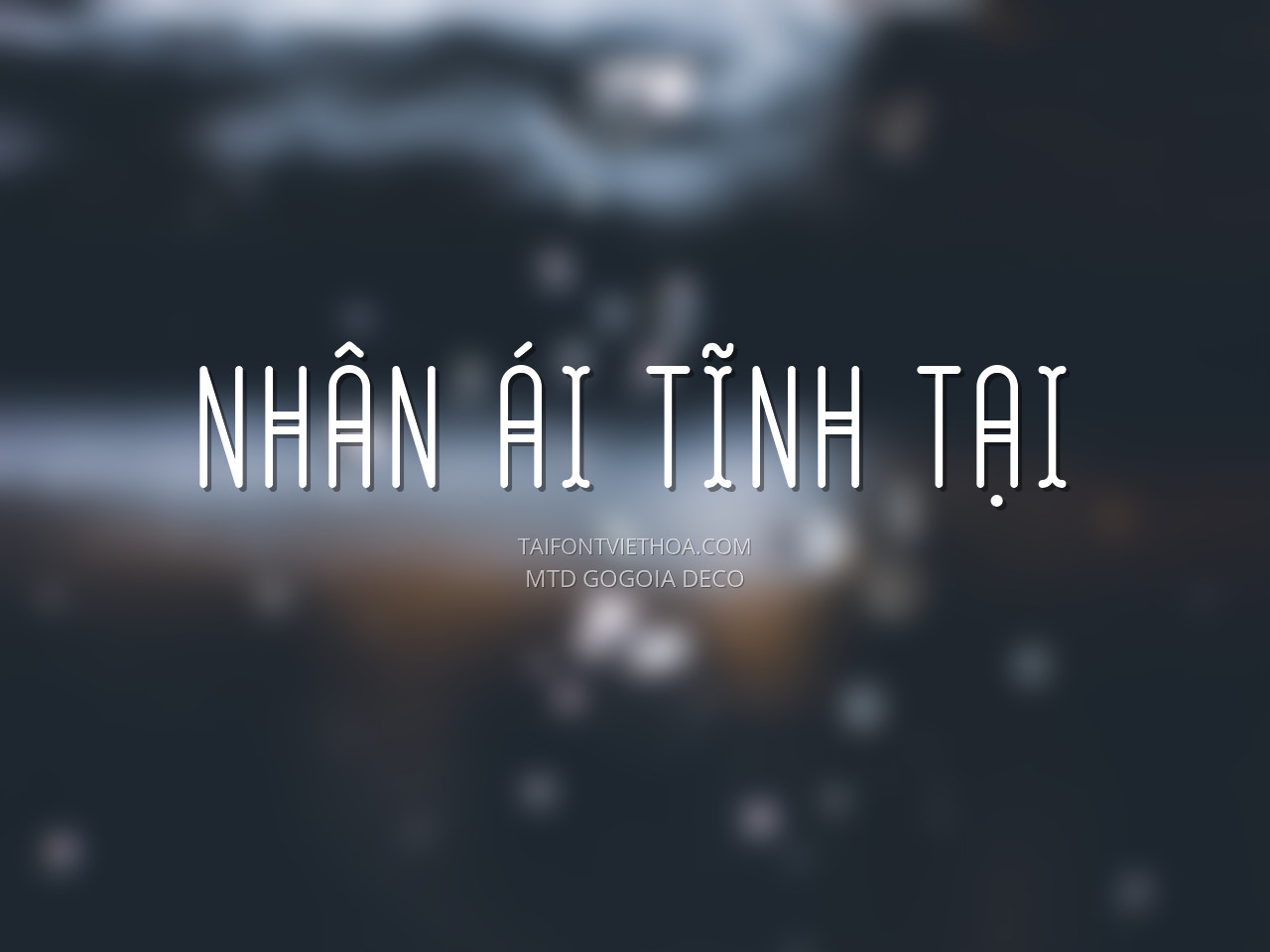
Giới thiệu về font Gogoia Deco
Gogoia Deco là một font display mang đậm phong cách hình học và nghệ thuật Art Deco, được thiết kế bởi Motokiwo Type (MTD). Font thể hiện sự kết hợp táo bạo giữa các khối hình học tối giản và tỷ lệ chữ lạ mắt, tạo nên cảm giác hiện đại, thời trang nhưng vẫn gợi nhớ nét hoài cổ của thập niên 1920–1940. Gogoia Deco không chỉ là một kiểu chữ mà còn là một yếu tố đồ họa độc đáo, phù hợp với những dự án đòi hỏi sự sáng tạo và khác biệt. Phiên bản Việt hóa do chính MTD thực hiện, hỗ trợ đầy đủ tiếng Việt và hơn 70 ngôn ngữ khác, mang lại tính linh hoạt cao cho nhà thiết kế trong và ngoài nước.
Font Gogoia Deco được taifontviethoa.com chọn lọc và giới thiệu trong nhóm font display ấn tượng, hướng đến cộng đồng sáng tạo đang tìm kiếm sự nổi bật và phá cách. Đây là một font có khả năng truyền tải ngôn ngữ thị giác rất mạnh, phù hợp với các dự án thương hiệu cá tính hoặc thiết kế nghệ thuật đậm dấu ấn cá nhân.
Đặc điểm thiết kế và ứng dụng của font Gogoia Deco
Font sở hữu thiết kế dạng khối, với các đường thẳng và góc bo tròn tinh tế, tạo ra sự cân bằng giữa cứng cáp và mềm mại. Mỗi ký tự như một tác phẩm hình học độc lập, mang đậm yếu tố nghệ thuật, dễ dàng thu hút ánh nhìn trong các thiết kế tiêu đề. Gogoia Deco không phù hợp cho văn bản dài nhưng lý tưởng cho các nội dung đòi hỏi tính thị giác cao và định vị phong cách riêng.
Ứng dụng lý tưởng: thiết kế poster, banner nghệ thuật, logo thời trang, bìa sách, bao bì mỹ phẩm, tiêu đề website sáng tạo, hoặc các sản phẩm thương hiệu cao cấp và nghệ thuật thị giác. Ngành nghề phù hợp: thời trang cao cấp, mỹ phẩm, nghệ thuật đương đại, thiết kế nội thất, nhiếp ảnh, lifestyle brand và các chiến dịch quảng cáo cần sự ấn tượng.